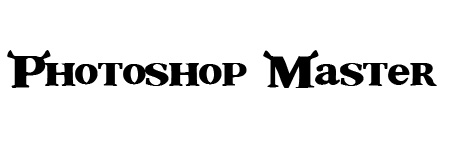
xDD похож на уши из Мультика Шрек
Такая надпись ещё в мультике шрэк
Очень мило и красиво*
Классный, но качать пожалуй не буду *О*
Ха, прикольно, но мне кажеться что-то не так, но не знаю что )))
Класс)
Ахах!Люблю Шрека!!:DDDDD
хах..забавно)
А,чё прикольно! Особенно если ставишь в отвратительно-зелёный! Сука,я гениален
хахах) класс.
косячный шрифт... символ "-" заменяет буквой "А"
Прикольно!
Шумветра, шрифт то БЕЗ поддержки русского языка))
У меня почему-то не получается писать этим шрифтом на русском языке..! На англисском все красиво, но как переключаюсь на русский, буквы становятся прозрачными...
Пригодится для детских коллажей.
это и есть ушы из "Мультика Шрек" :D
ужассс.. я скачиваю... хД
хах)Прикольн